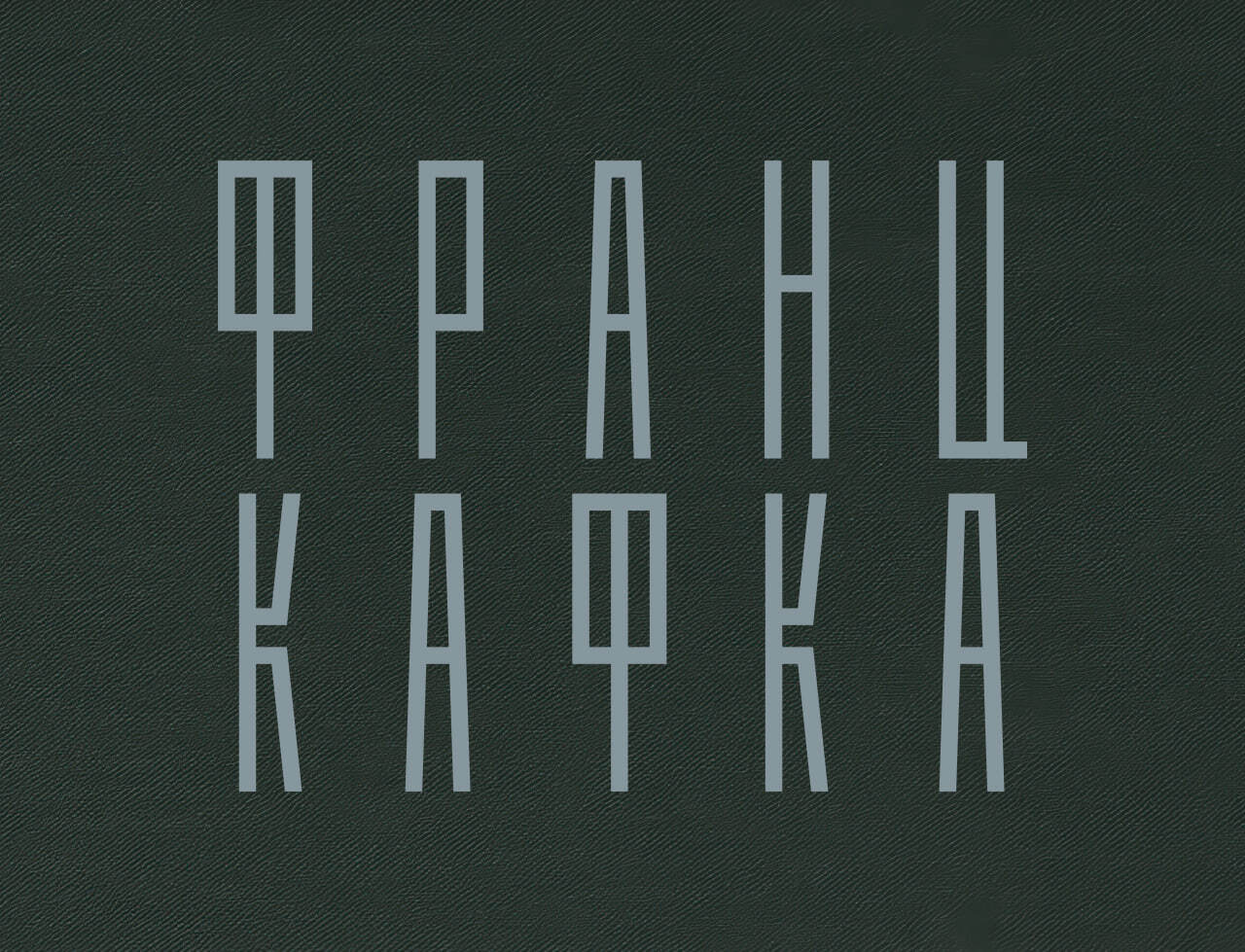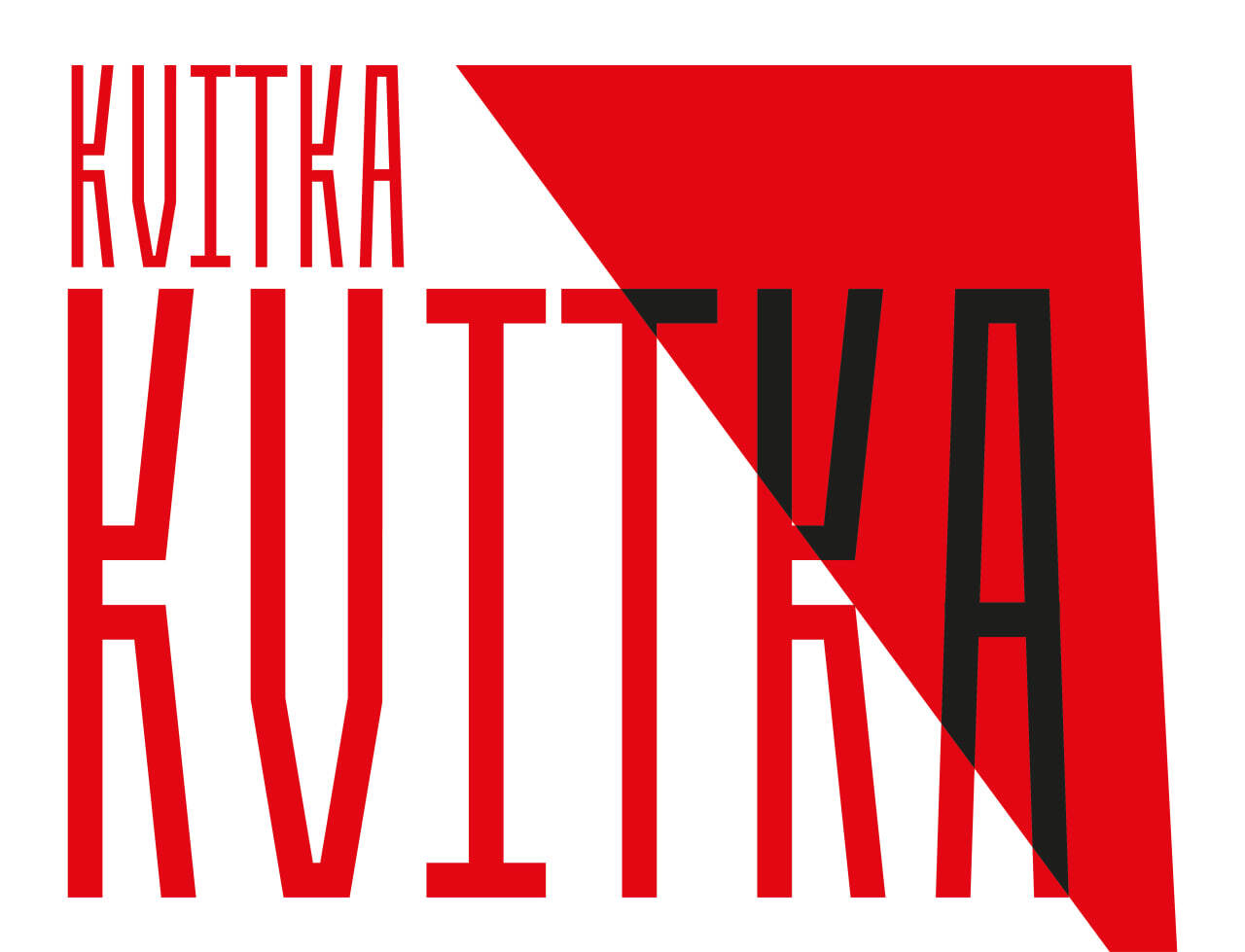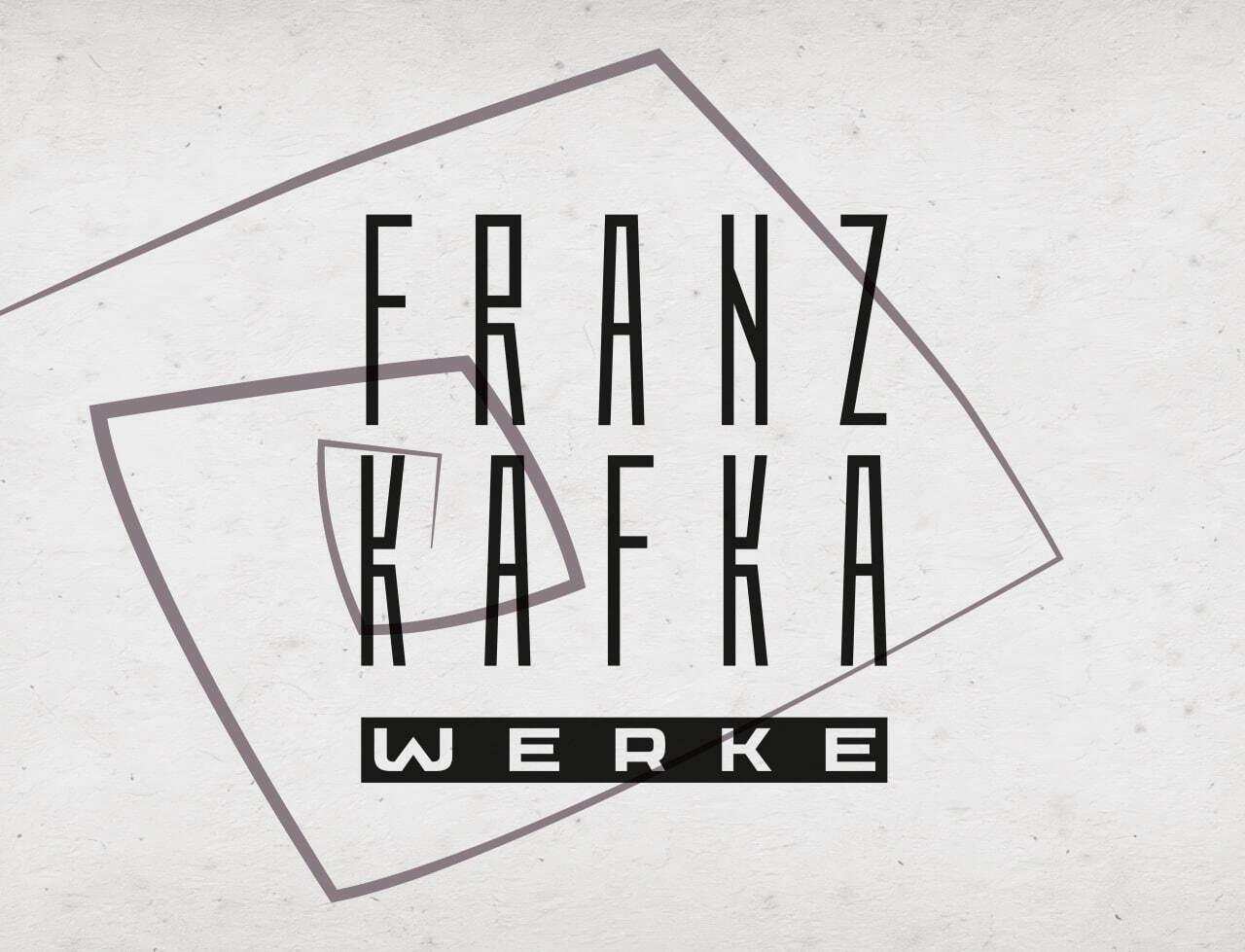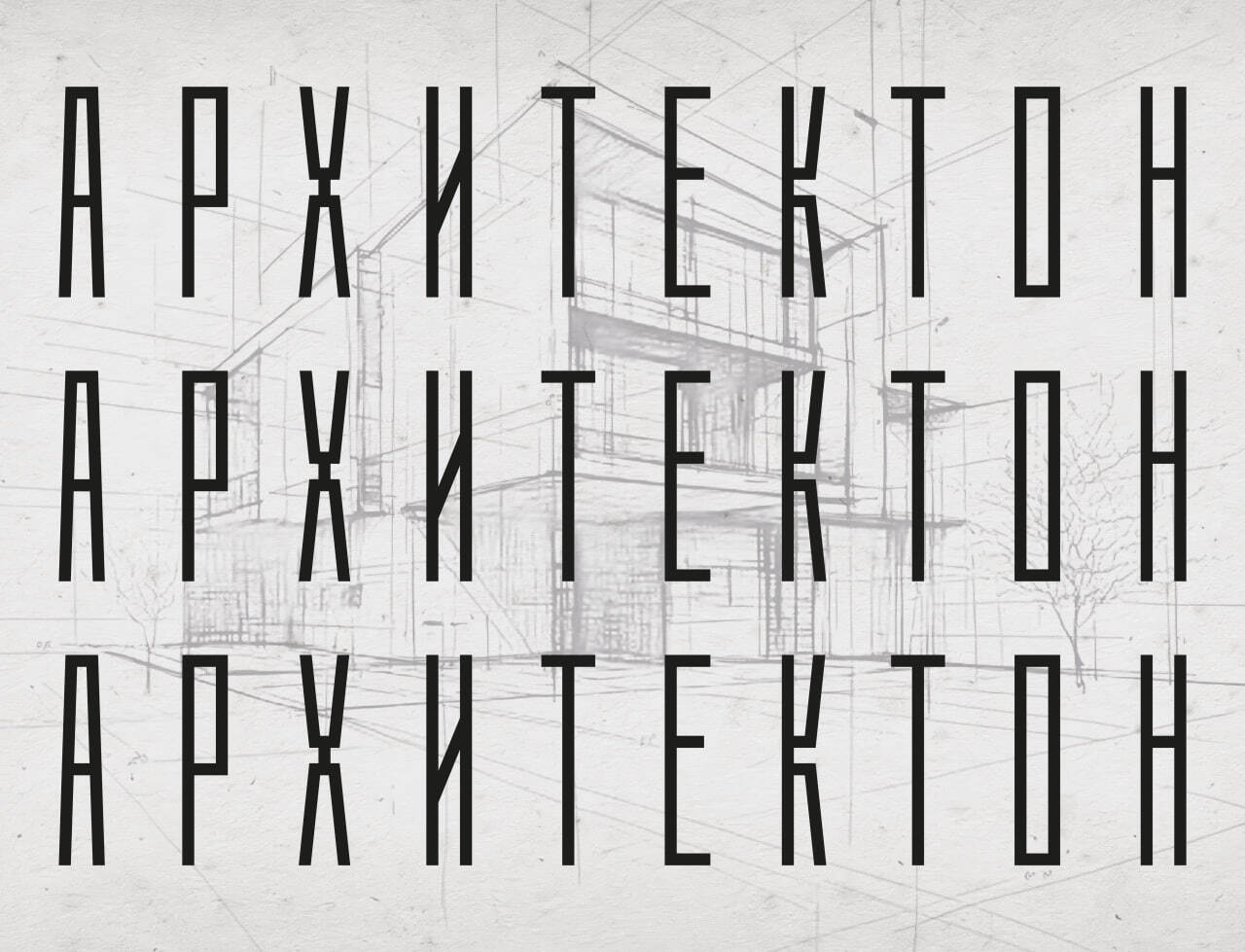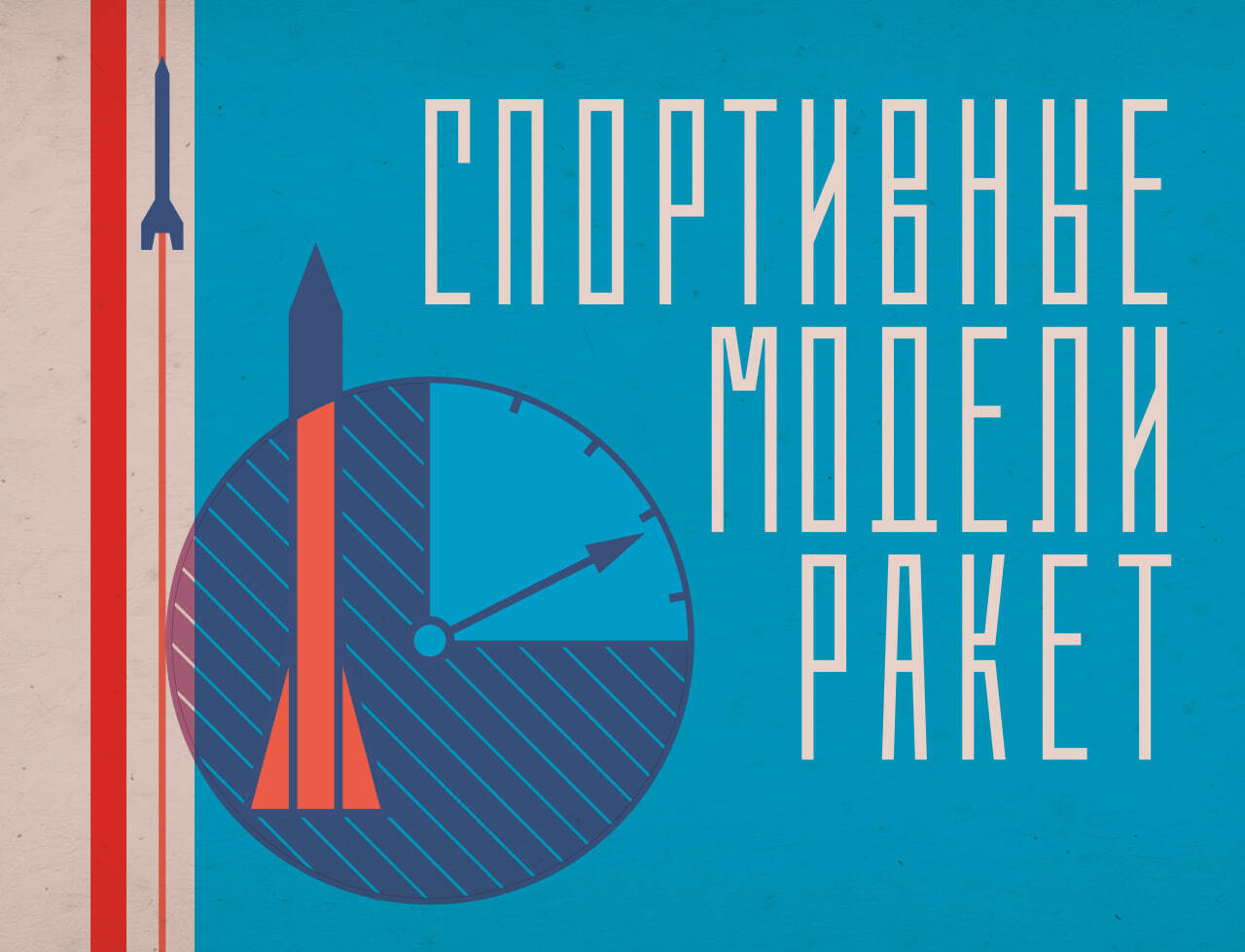
Шрифт Квитка
Kvitka — узкий акцидентный шрифт с подчёркнутой вертикальностью и симметрией, близкой конструктивистским экспериментам начала XX века. Внутри знаков всё подчинено одной жёсткой логике, отчего набор звучит сдержанно и почти отстранённо. Логотипы, плакаты и заголовки об архитектуре, модернизме, философии и внутреннем отчуждении получают с ним нужную интонацию. В комплекте — полная версия STAR и лицензия.